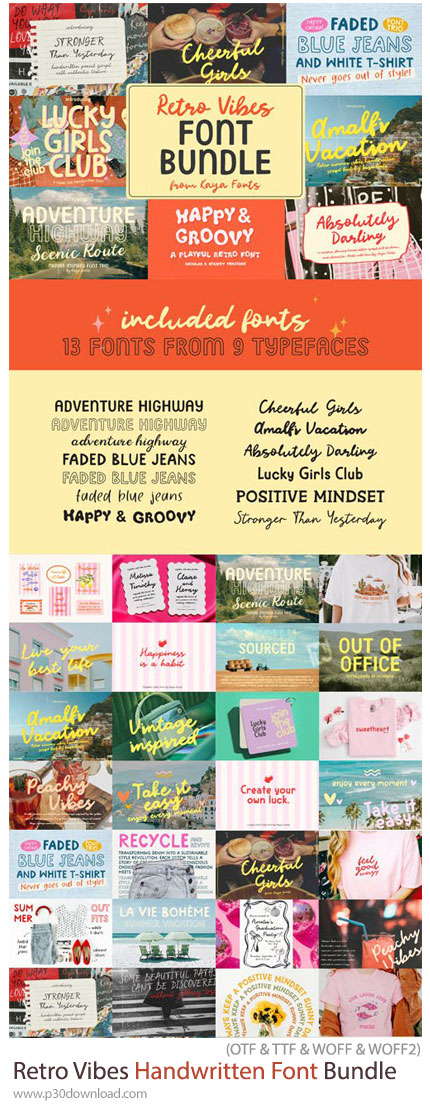
دانلود Retro Vibes Handwritten Font Bundle مجموعه فونت دستنویس رترو
در این بخش شاهد مجموعه فونت دستنویس رترو می باشید که با فرمت های OTF و TTF و WOFF و WOFF2 بر روی سایت برای دانلود قرار گرفته است. Retro Vibes Handwritten Font Bundle یک پکیج حرفهای شامل 13 فونت پریمیوم دستنویس (Handwritten Fonts) با استایل رترو، وینتیج و نوستالژیک است که برای طراحیهای خلاقانه، برندینگ و پروژههای گرافیکی خاص ساخته شده است. این مجموعه حس گرم، انسانی و قدیمی به طراحیهای دیجیتال اضافه میکند و برای پروژههایی با حالوهوای کلاسیک و هنری بسیار مناسب است. Retro Vibes Handwritten Font Bundle یک مجموعه کامل از فونتهای دستنویس با حالوهوای رترو است که به طراحیهای شما حس صمیمیت، نوستالژی و شخصیت هنری میدهد.
ویژگیهای کلیدی:
- شامل 13 فونت دستنویس پریمیوم
- سبک رترو، وینتیج و کلاسیک
- مناسب طراحیهای هنری و خلاقانه
- مناسب پروژههای چاپی و دیجیتال
- خوانایی بالا همراه با استایل هنری
کاربردها:
- پست و استوری شبکههای اجتماعی
- موشن گرافیک و ویدیوهای تایپوگرافی
- طراحی جلد کتاب و مجلات
- پوسترهای هنری و تبلیغاتی
- طراحی کارتهای دعوت و هدیه
- برندینگ سبک Vintage / Retro
مناسب برای:
- طراحان گرافیک
- موشن دیزاینرها
- تولیدکنندگان محتوا
- برندهای هنری و سبک رترو
- فریلنسرهای طراحی
- عکاسان و آرتیستهای دیجیتال